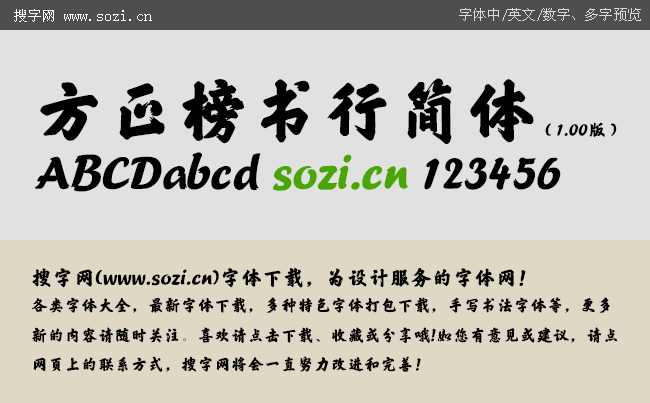
方正榜書行簡(jiǎn)體
搜字網(wǎng)提供一款方正榜書行簡(jiǎn)體中文書法字體下載,方正榜書行簡(jiǎn)體是一款手寫風(fēng)格的中文藝術(shù)字體,字形瀟灑大方,醒目流暢,整體效果非常不錯(cuò),可以應(yīng)用于廣告設(shè)計(jì)、包裝印刷、產(chǎn)品設(shè)計(jì)、海報(bào)設(shè)計(jì)等方面,有喜歡的朋友可免費(fèi)下載收藏。